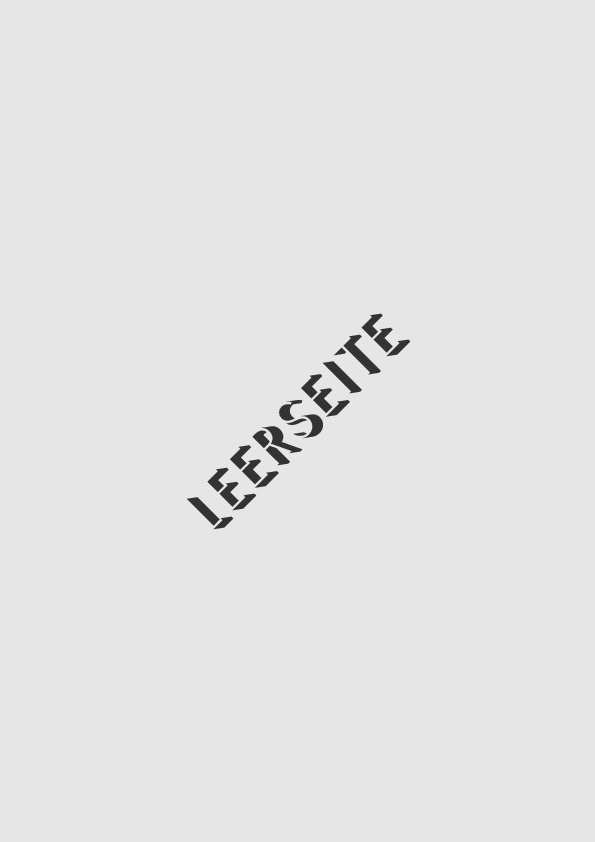
Leere Seite verschwindet im Druck
ich habe eine wahrscheinlich dämliche Frage, aber ich finde einfach nichts. In QX 15 habe ich ein Printbuch erstellt. Diese soll ein paar Leerseiten haben, wo auch keine Seitenzahl zu sehen ist. Das klappt alles wunderbar. Nur leider habe ich früher mal die Erfahrung gemacht, dass das eine Onlinedruckerei die leeren Seiten "gelöscht" hat, sodass der ganze Satz verrutscht ist. Wie kann ich das verhindern? Gibt es eine Funktion die diese leeren Seiten schützt?
Wenn die leeren Seiten in deinem Druck-pdf enthalten sind, muss die Druckerei sie auch berücksichtigen. Sonst ist’s deren Fehler und sie machen es halt auf ihre Kosten nochmal.
Liebe Schreibfee, ich stimme bertel zu. Ich setze seit 15 Jahren und habe schon alle möglichen Probleme mit Druckereien erlebt, aber mir hat noch keine Druckerei Vakatseiten gelöscht, die in der PDF-Datei angelegt waren. Dass dieser Fehler passiert, kann ich mir einfach nicht vorstellen. Manchmal werden eher noch leere Seiten angehängt, um die Seitenzahl auf den korrekten Wert (meist teilbar durch vier) aufzufüllen.
Könnte es sein, das der Hinweis "this page intentionally left blank" in vielen Hardware-Manuals eben genau dieses Aussortieren von Vakatseiten verhindern soll? - wobei die Seite genau genommen dann ja gar nicht mehr "left blank" ist...
Na ja, ich hatte das immer eher als Hinweis an die Leser interpretiert, damit die ein vermeintlich unvollständig gedrucktes Buch nicht reklamieren.
So hab ich das auch immer aufgefasst.
Ich habe in meinen zusammengestückelten PDF-Mappen für so was immer eine „Leerseite“ eingefügt. Die geht diagonal von links unten nach rechts oben über das Blatt, ist eine graue Schattenschrift. Genauer genommen die Semplicità Ombra:
Typeface:	Semplicità
Designer:	Alessandro Butti
Year:		1930
Publisher:	Nebiolo foundry
Wird in Italien als Schrift der Faschisten gesehen.
Gestolpert bin ich über diese Schrift im Zusammenhang mit den Tannenberg-Faden ...
Statt Hellgrau kann man das natürlich auch in Hellweiß setzen.  :baeh:
Kommt dann toll auf dunkelweißem Papier :-)